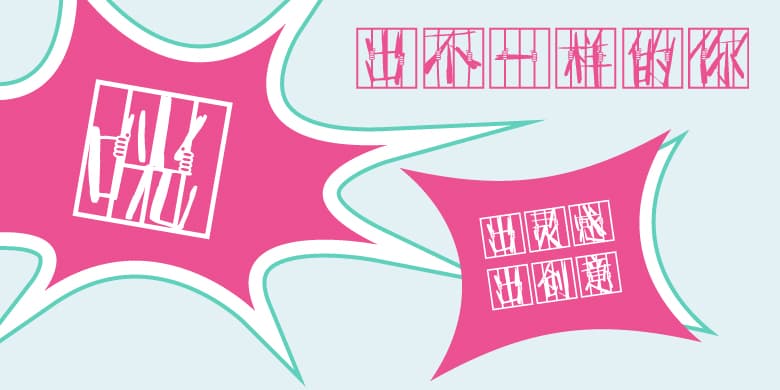
品牌:方正字库设计师:于彦舒发行时间:2020字库编码:大陆简体(GB2312-80)分类:创意书写字体属性:精品字
方正duang体 由漫画家于彦舒在方正呐喊体的基础上做的二次创作,试图表达一种呐喊、自嘲、发泄、冲破束缚的情感,来排解年轻人在网络生活中的负面情绪。这款字体的笔画刚硬狂野,与浮动的方框、铁窗形成鲜明的对比,如一个人强烈试图挣脱某种困境。